上首松羽体字形是借鉴了弯刀其独特曲线和力学原理,字体的每个笔画都沿用了其特点;横笔的突出梯形角代表着稳重握柄,竖笔的月牙代表着皎洁弯月的刀身,转折的部分则以刀尖加以装饰,整体着重表现了字体的独特之处,使字体增加了其审美性及文化性。
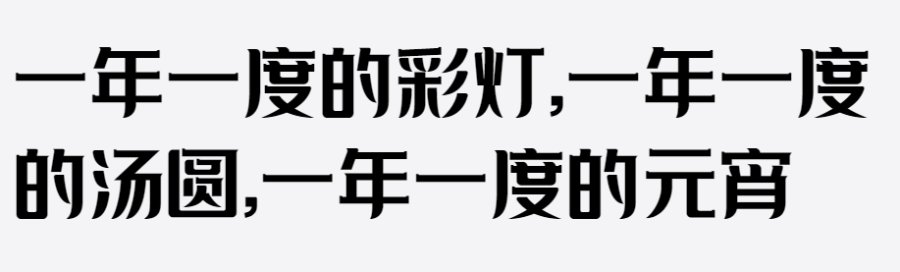
上首燕尾体整体字型方正,具有稳重的感觉;同时所有字体右上角增加小角,具有灵动飘逸的视觉效果。
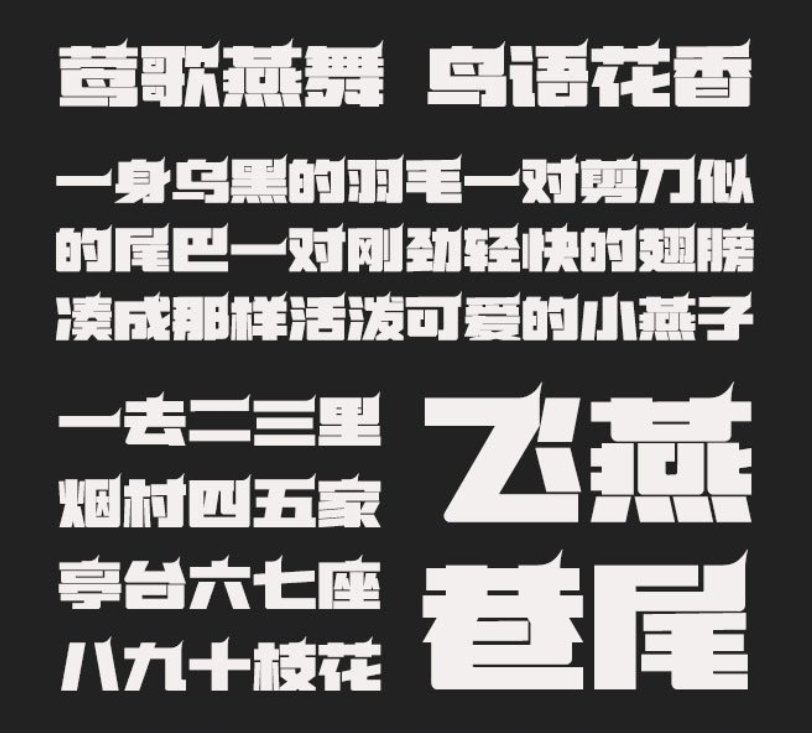
上首韶华体字体笔画纤细优美,横笔画更为纤细,单整体对比不大,给人一种简约又不失可爱的感觉,字形如花一般的女子,正值青春美好的时光。